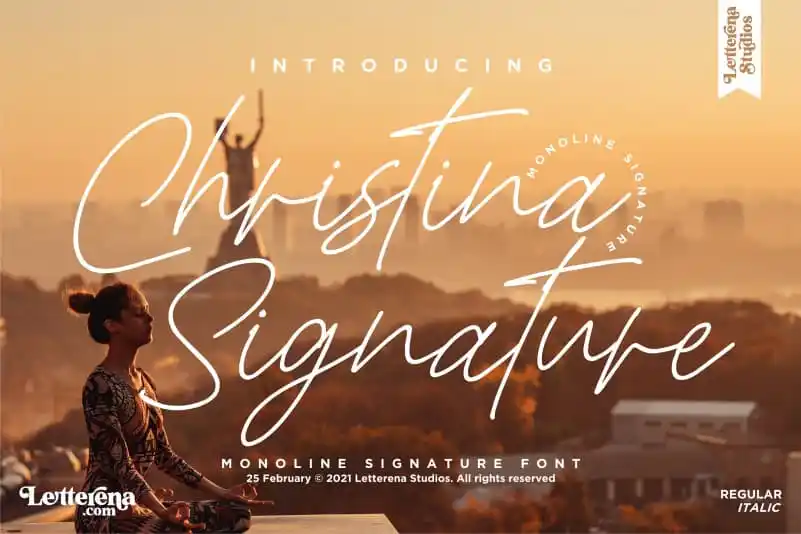
Christina Signature Script Font – Download Grátis
A fonte Christina Signature Script é uma opção irresistível para aqueles que buscam adicionar um toque único à sua próxima obra de arte digital ou impressão. Com seu traçado elegante e fluido, essa fonte é perfeita tanto para criar logos memoráveis quanto para projetos de embalagens ou ilustrações, garantindo que cada trabalho tenha um sabor autêntico e sofisticado. Seja para personalizar uma camiseta de evento especial, adornar uma capa de livro com estilo, adicionar uma frase inspiradora em uma mala de viagem ou até mesmo criar um design exclusivo de cartão de convite, a Christina Signature Script pode transformar qualquer projeto em algo excepcional. Sua versatilidade faz dela uma escolha inteligente para qualquer aplicação que exija um toque de script signature elegante e sofisticado. A designer letterenastudios cria este recurso gráfico com paixão, cuidando meticulosamente da forma e do estilo para criar o máximo impacto. A fonte é ideal tanto para aqueles buscando algo criativo e autêntico quanto para quem busca um toque de luxo em seus projetos digitais ou impressos. Com Christina Signature Script, suas criações assumem uma nova personalidade, oferecendo a oportunidade de expressar sua individualidade através do design.